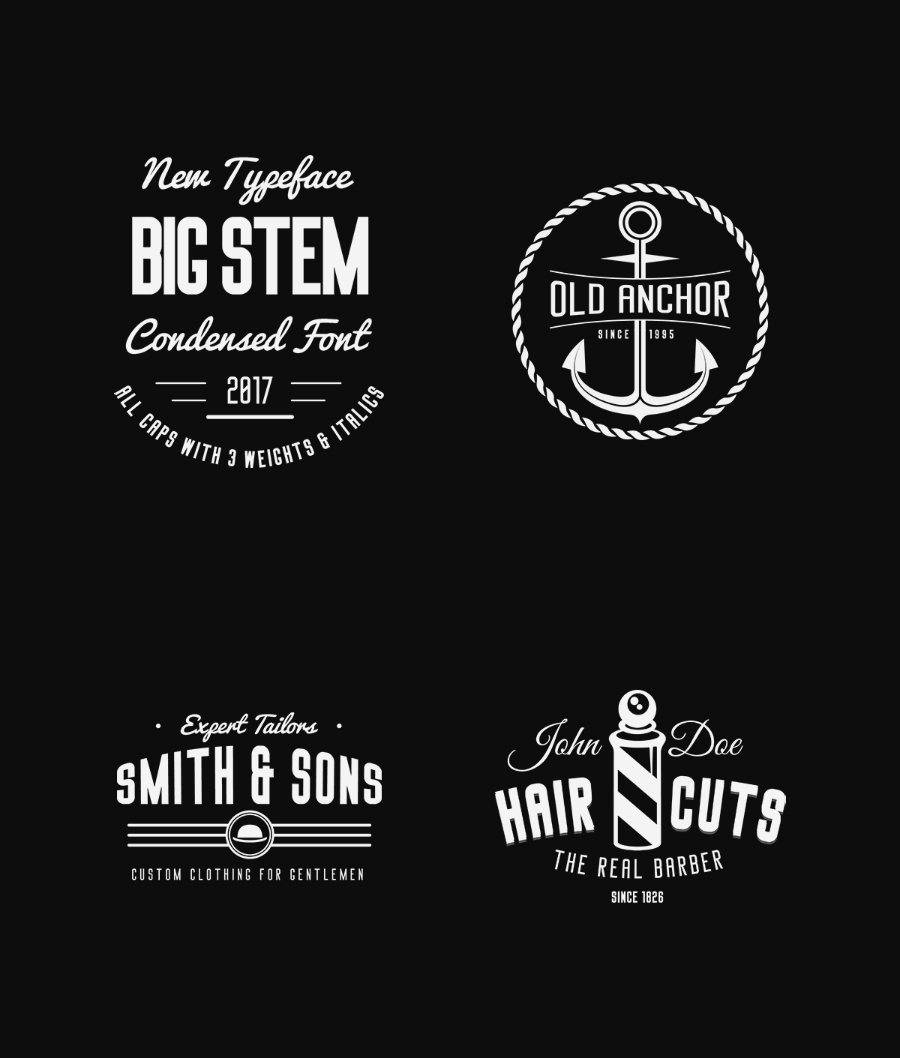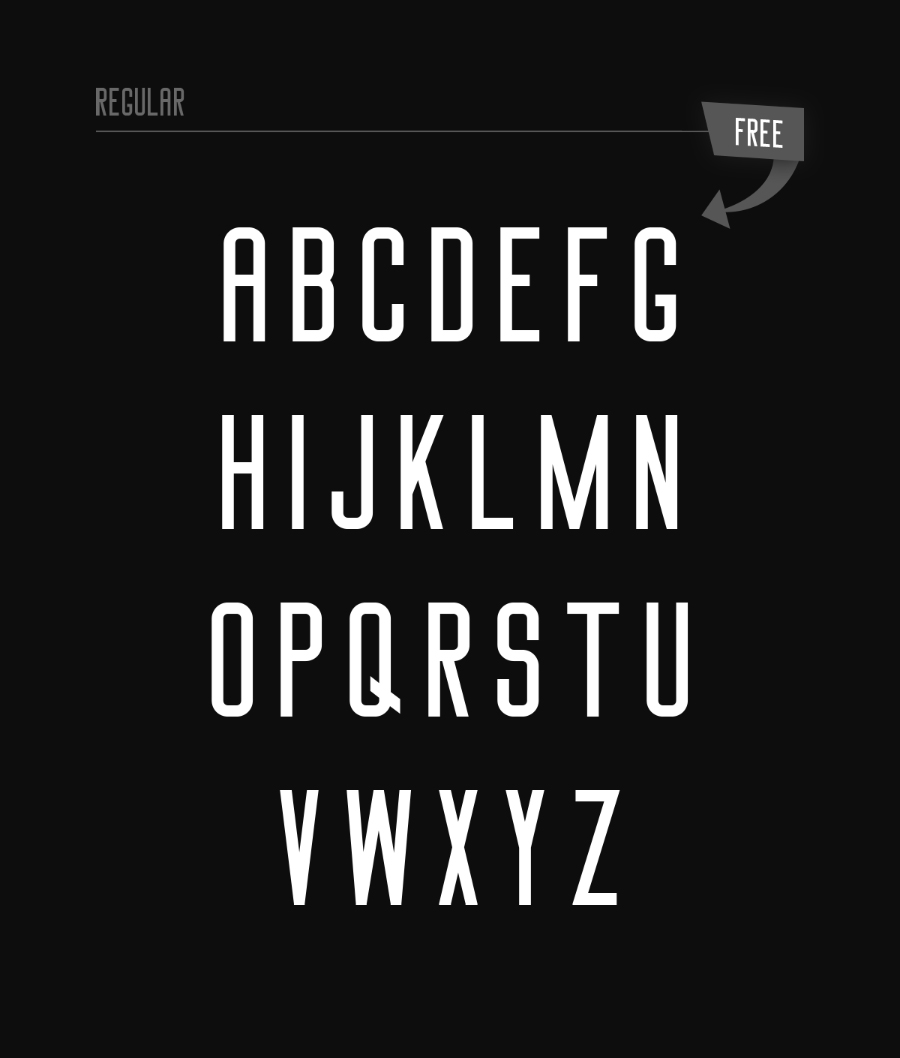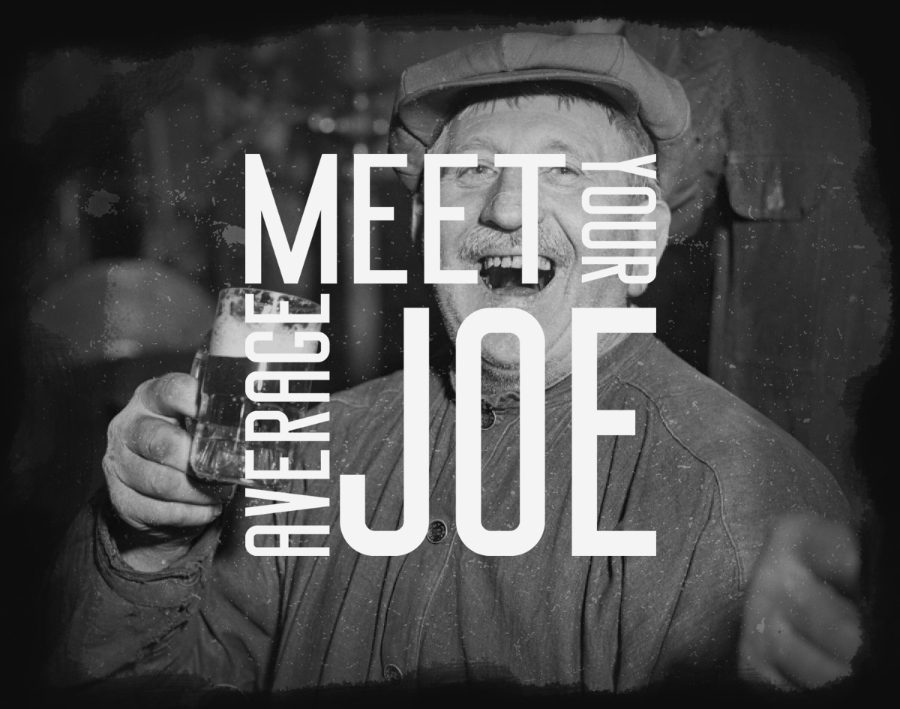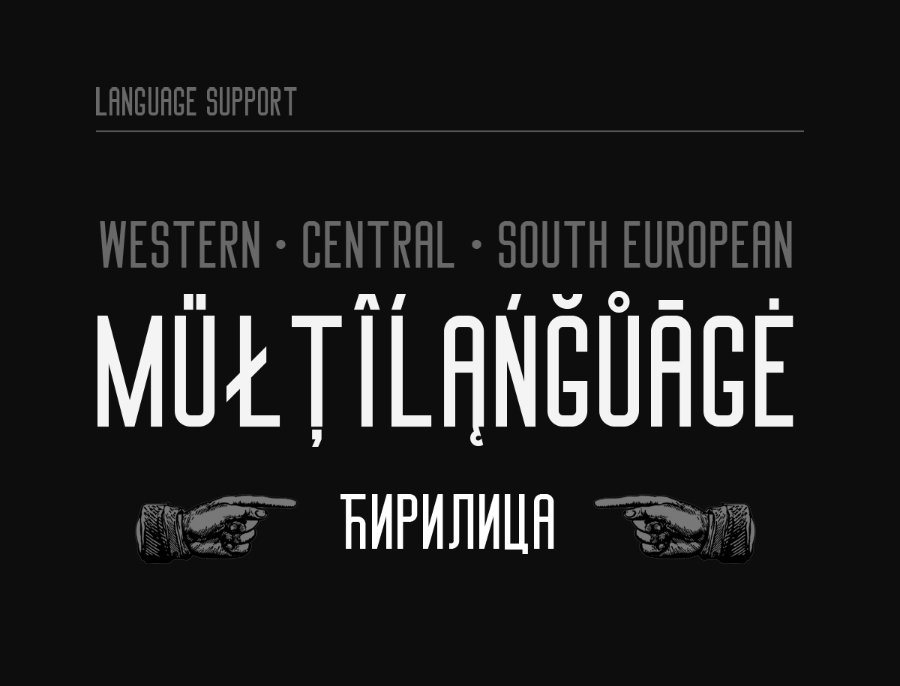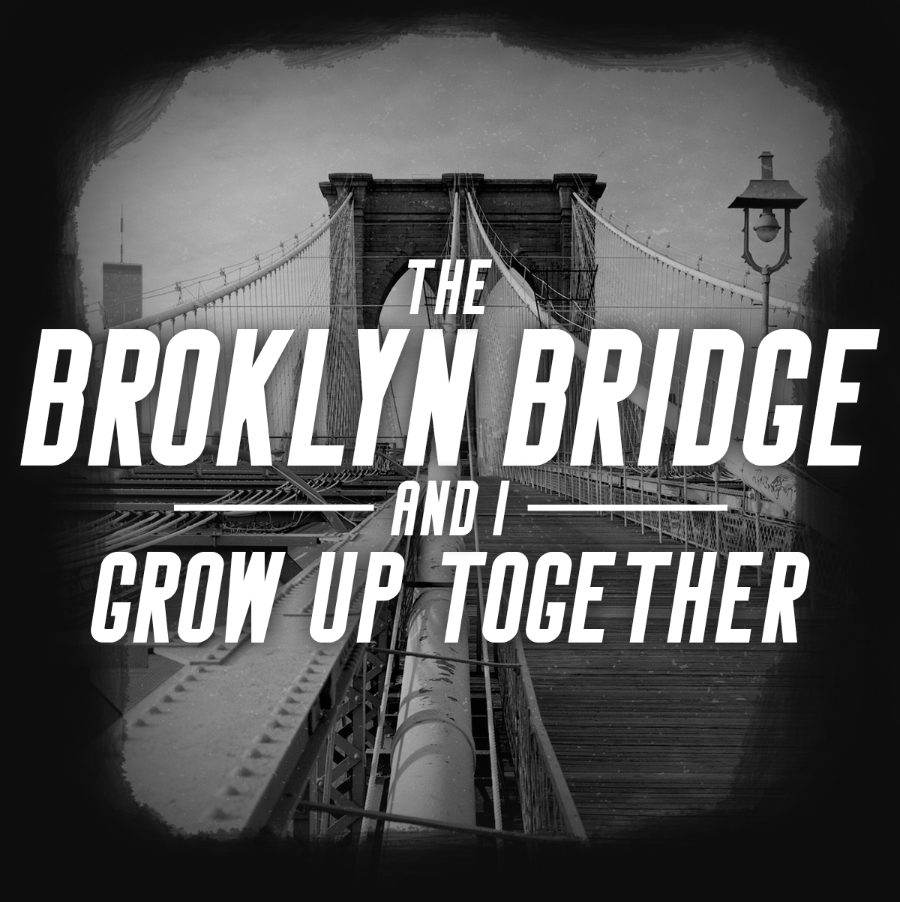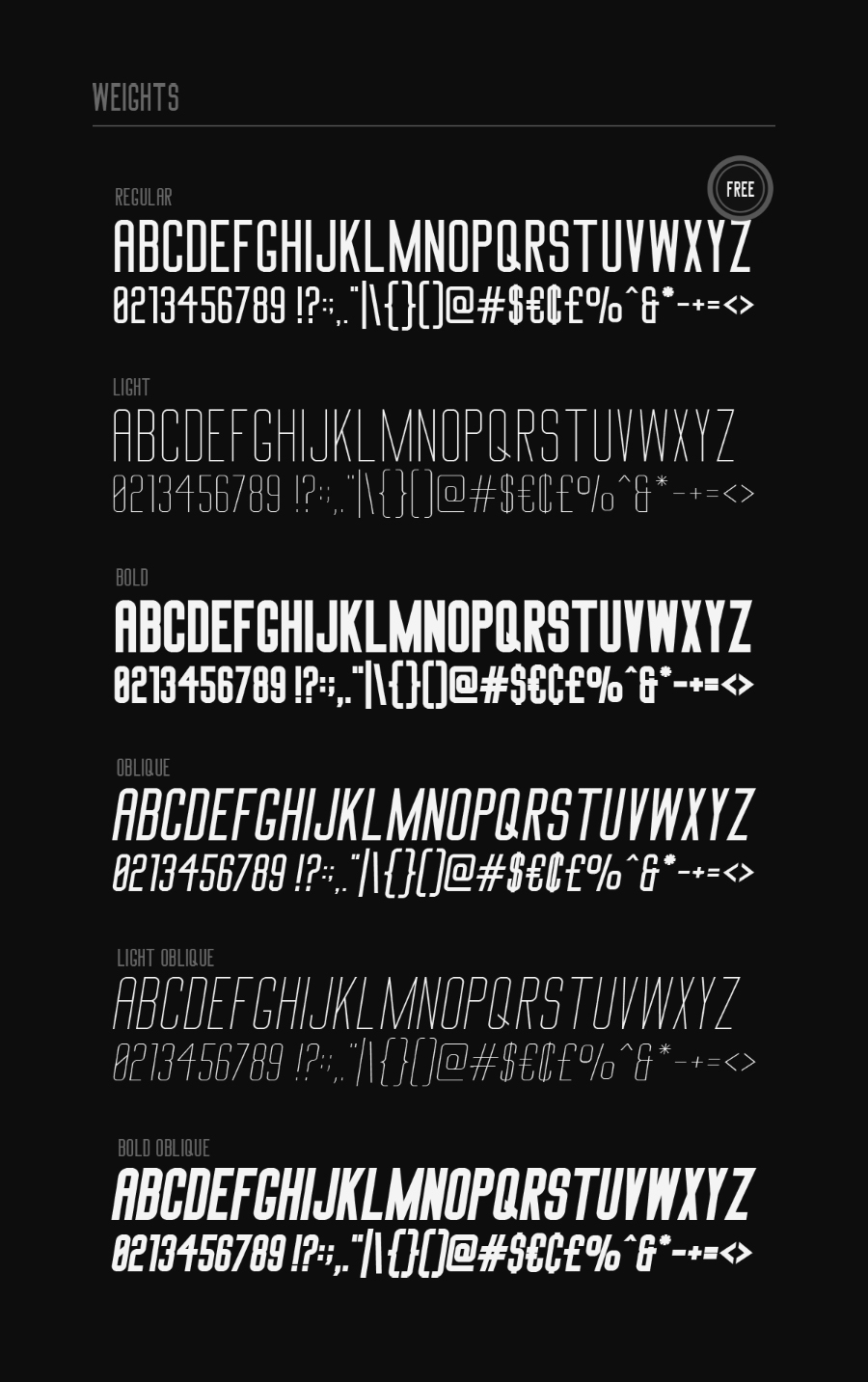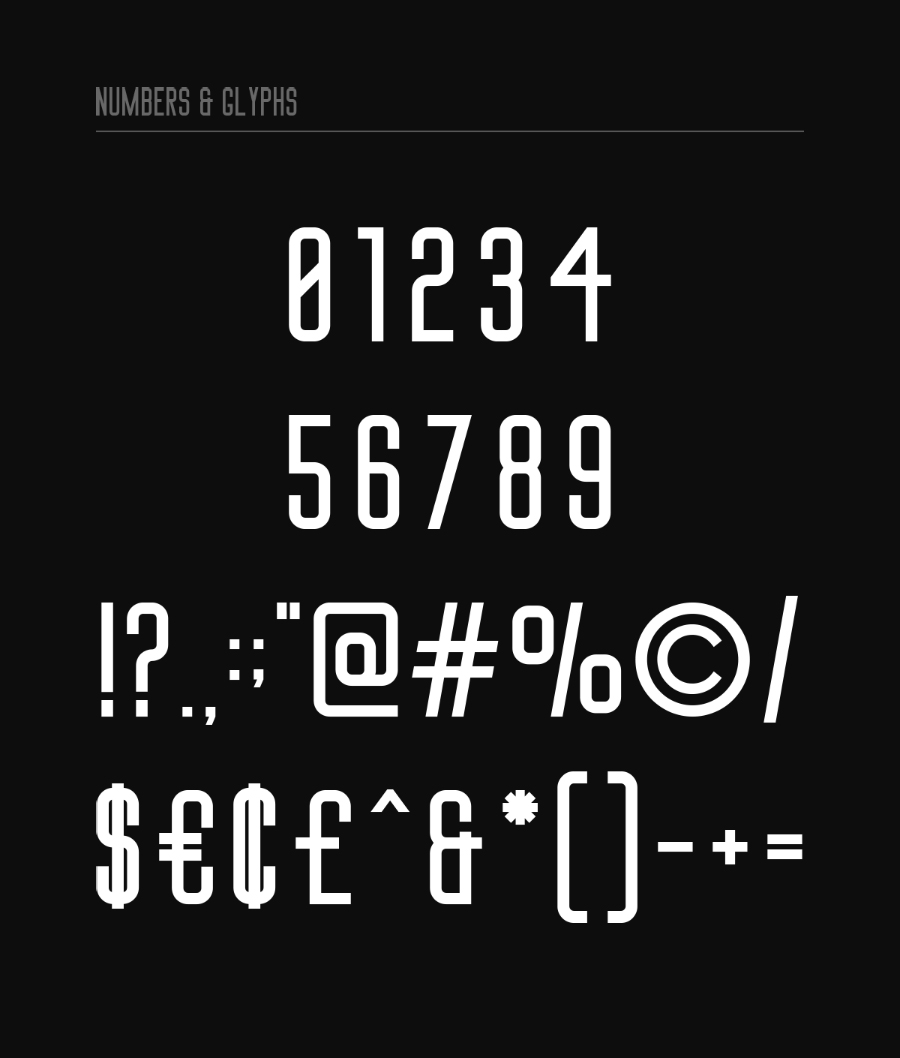
大干免费演示字体
今天,您可以从Boris Garic的最新作品中获得Big Stem Free Demo字体。 Big Stem是一个全部浓缩的字体。它的大,强大和强大适合标题,海报,标题和标题。 Big Stem有6种重量,支持语言。那么,在这里,你可以有一个来自家庭的Big Stem Regular。所以,现在下载,你可以发现自己有多好。